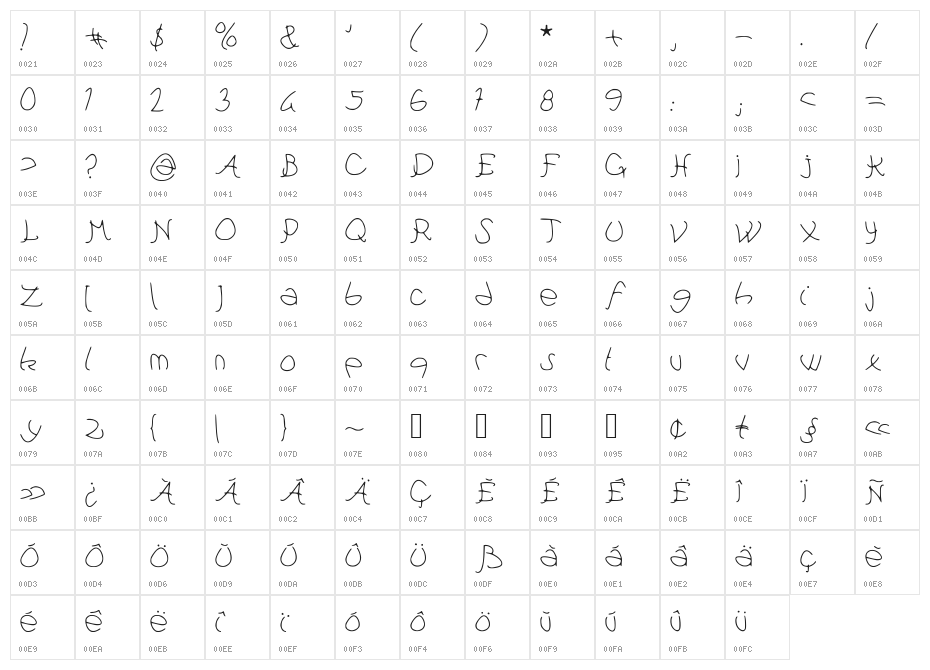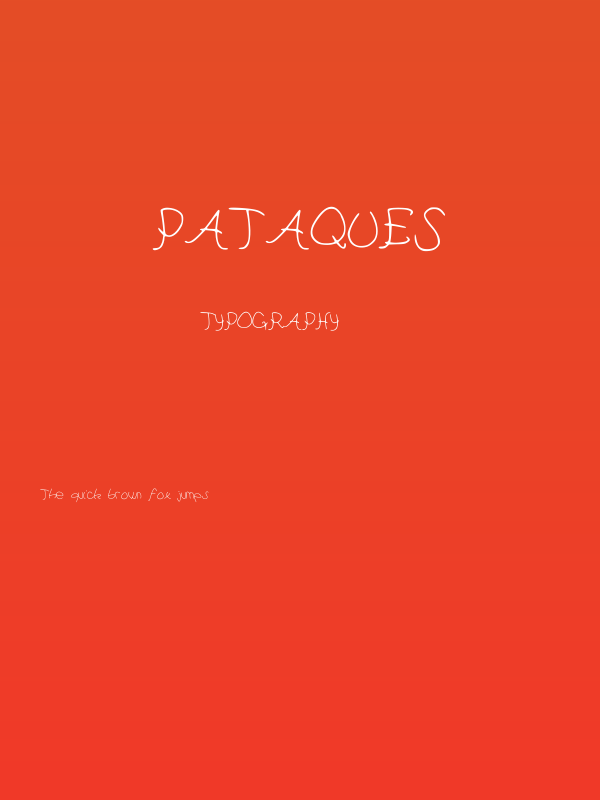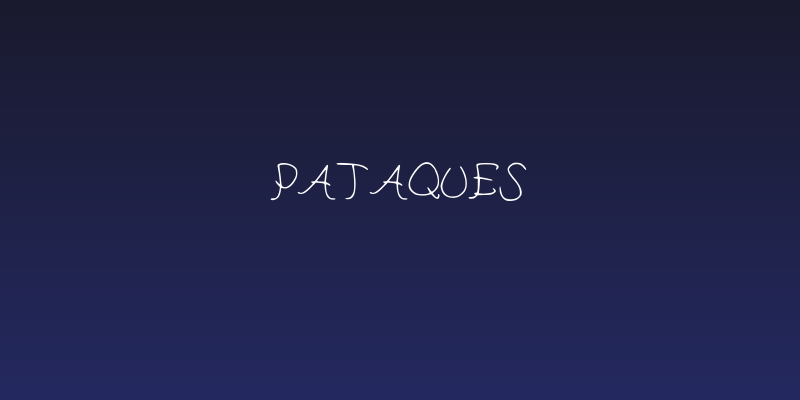
Pataques Font
| Gesamtstil | Casual, Playful |
| Anwendungsfall | Headlines, Creative projects, Informal text |
| Vorgeschlagene Projekte | Ideal for greeting cards, invitations, children's books, and creative branding. |